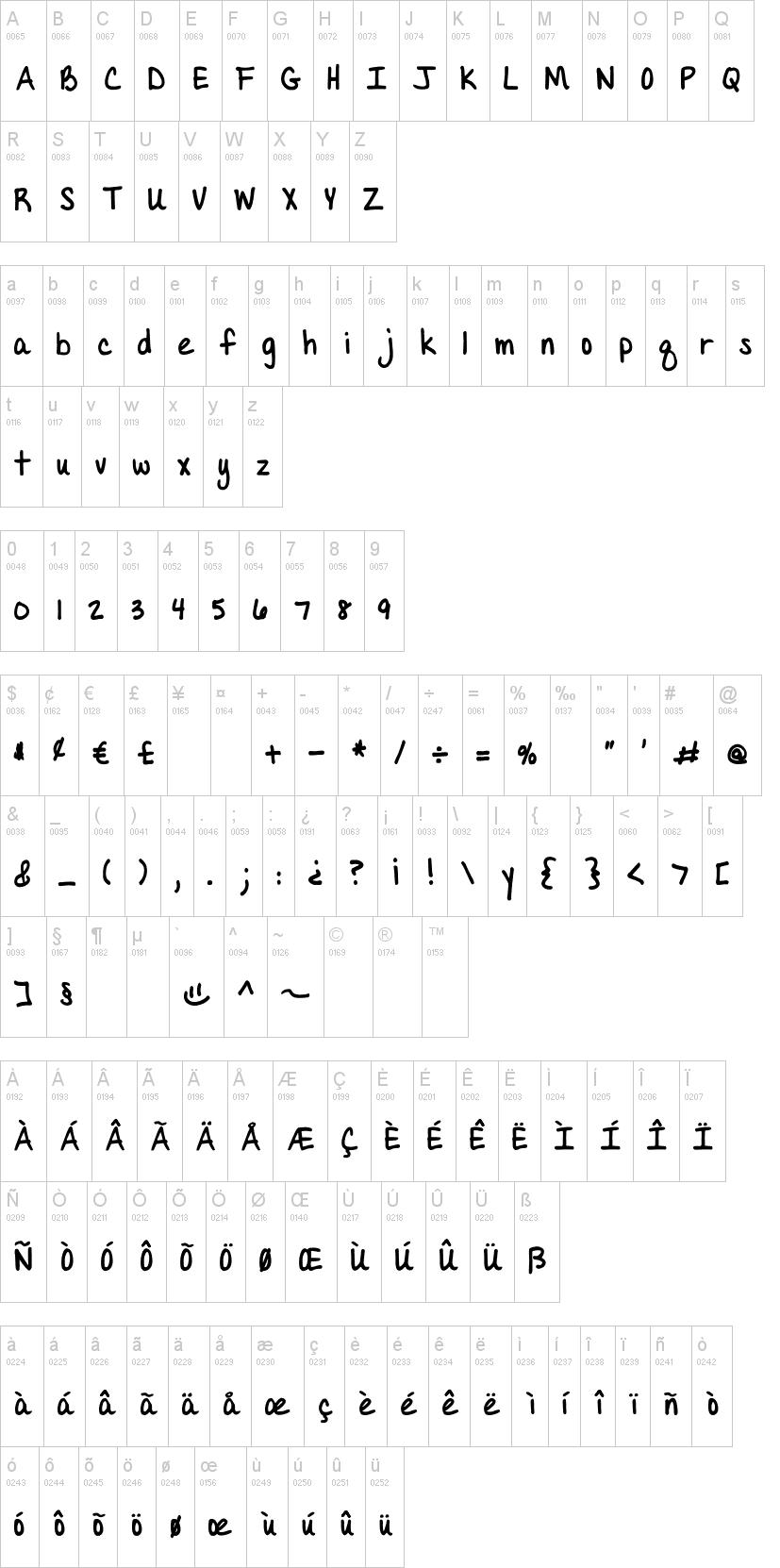
DJB Almost Perfect是一种手写风格的字体,由美国设计师Darcy Baldwin创建。这种字体的设计灵感来自于Darcy Baldwin自己的手写字体,因此它看起来非常自然、亲近和独特。DJB Almost Perfect字体具有非常明显的手写笔画,使得它非常适合用于卡片、海报、标签等场合。 这个字体包含了大量的字形,包括大小写字母、数字、标点符号和特殊符号。它的字形有些毛糙不够光滑,这是为了强调手写的感觉。此外,DJB Almost Perfect字体还包含了一些额外的手写元素,如小花、箭头、心形和星星等,使得这个字体更加富有趣味性和创意性。 总的来说,DJB Almost Perfect字体是一种非常适合用于手写风格设计的字体,它能够为设计师带来非常独特的视觉效果。内容介绍
DJB Almost Perfect是一款非常不错的手写艺术字体,具有很好的视觉感,适合于文化类的宣传设计、商业类品牌的广告和产品包装设计以及个性化文字排版等较多场景。